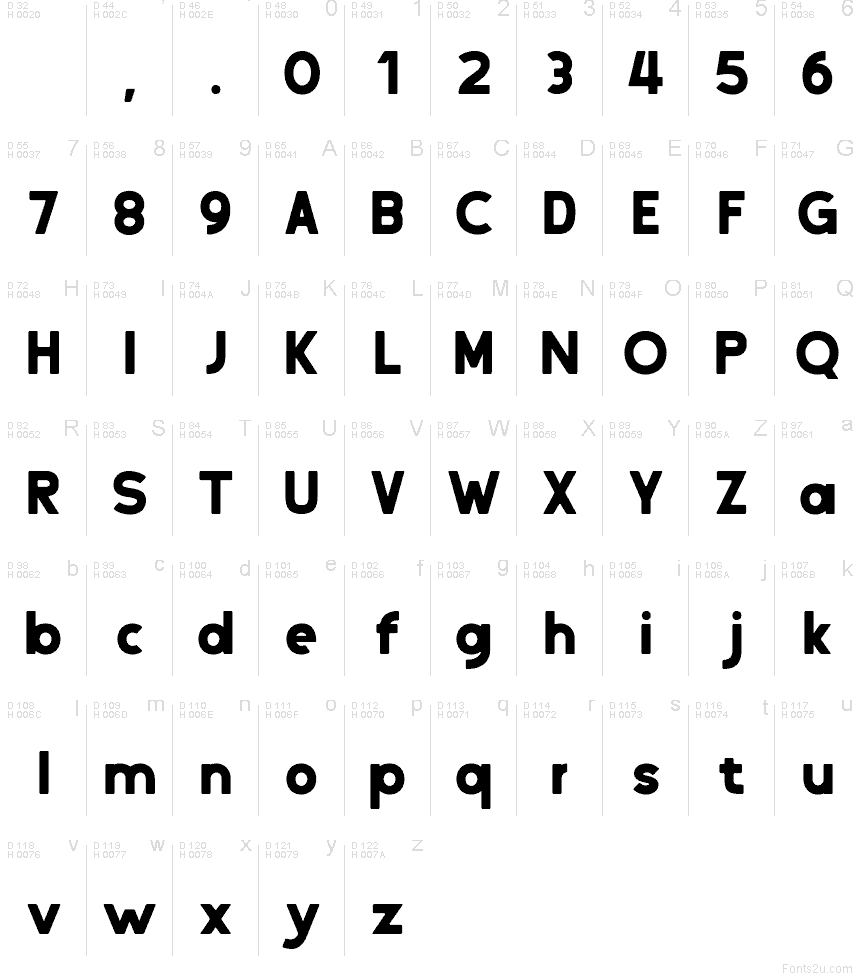
Auroxa Regular
Auroxa von Muksal Creative ist eine kostenlose serifenlose Schrift mit breiten, abgerundeten Formen und einfachen geometrischen Kurven. Ihre Buchstaben bewahren eine stabile, runde Konstruktion mit offenen Punzen und weichen Ecken, die dem Schriftbild einen kompakten, blockartigen Rhythmus verleihen.
Auroxa eignet sich hervorragend für Logodesigns, Plakatüberschriften, App-Branding, Verpackungen, Social-Media-Grafiken und kurzen Anzeigentext, da die fließenden Formen in jedem Buchstaben konsistent bleiben. Diese kostenlose Schrift bringt eine aufgeräumte, zugängliche Struktur in Layouts, die eine einfache serifenlose Schrift mit mehr Charakter als ein Standardsystemfont benötigen.